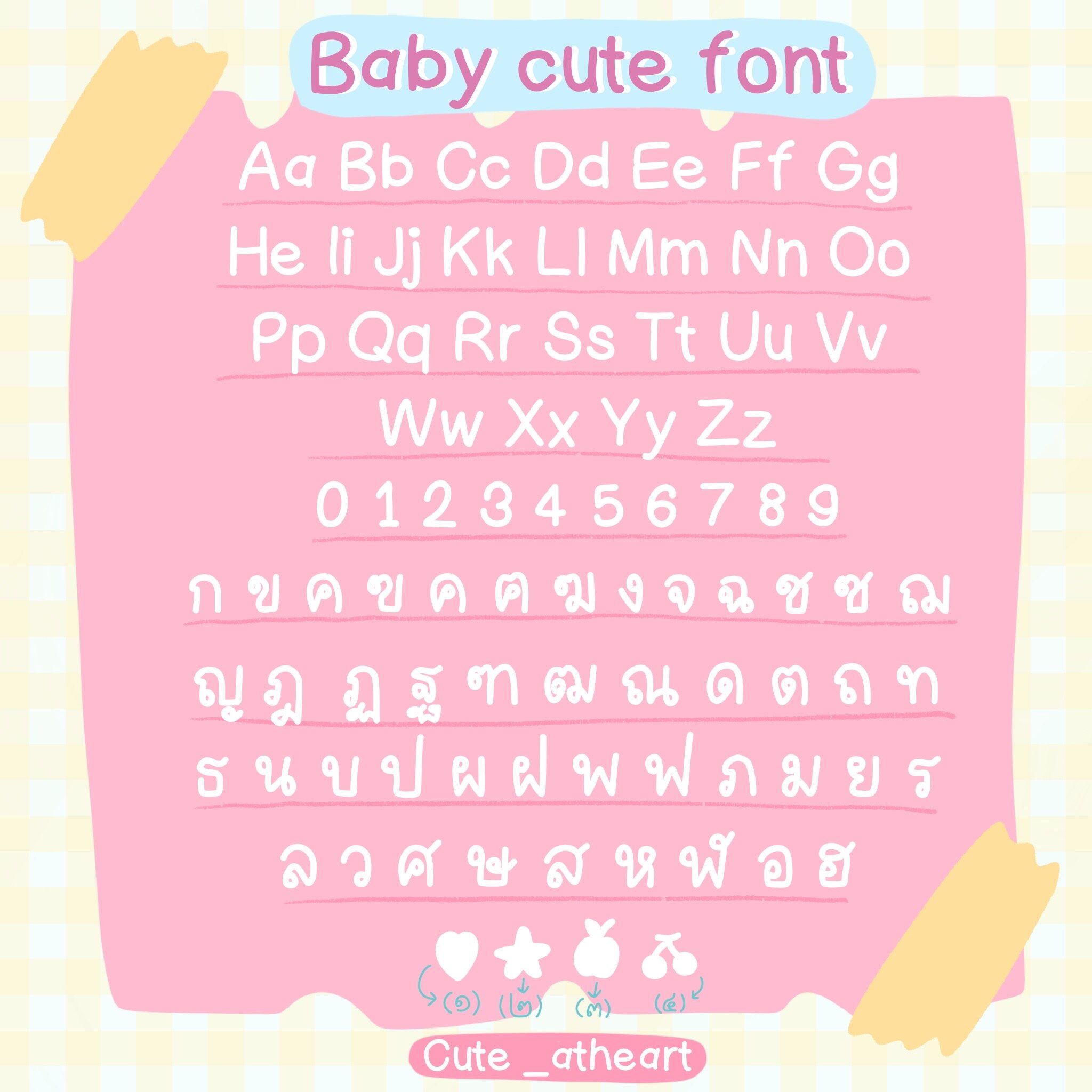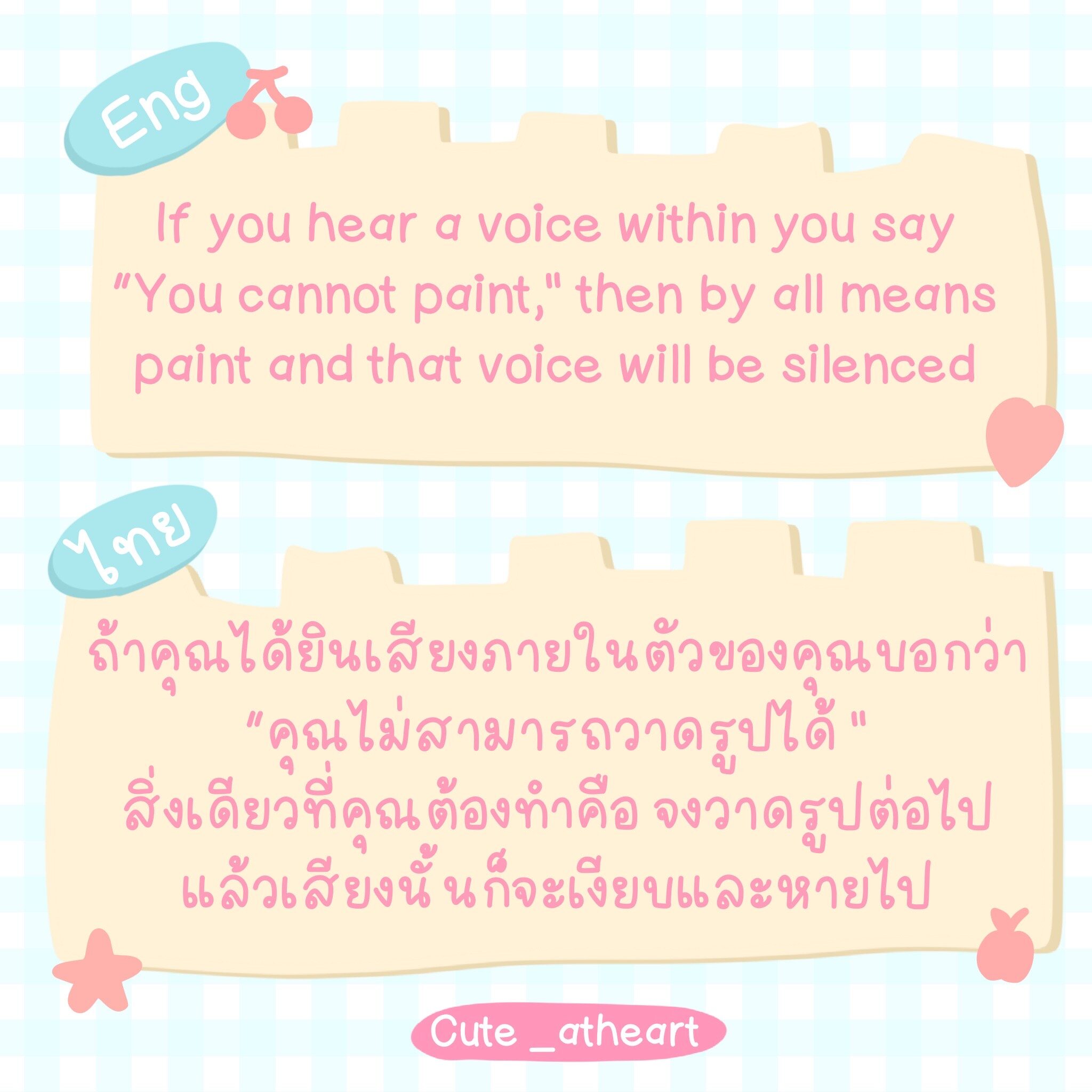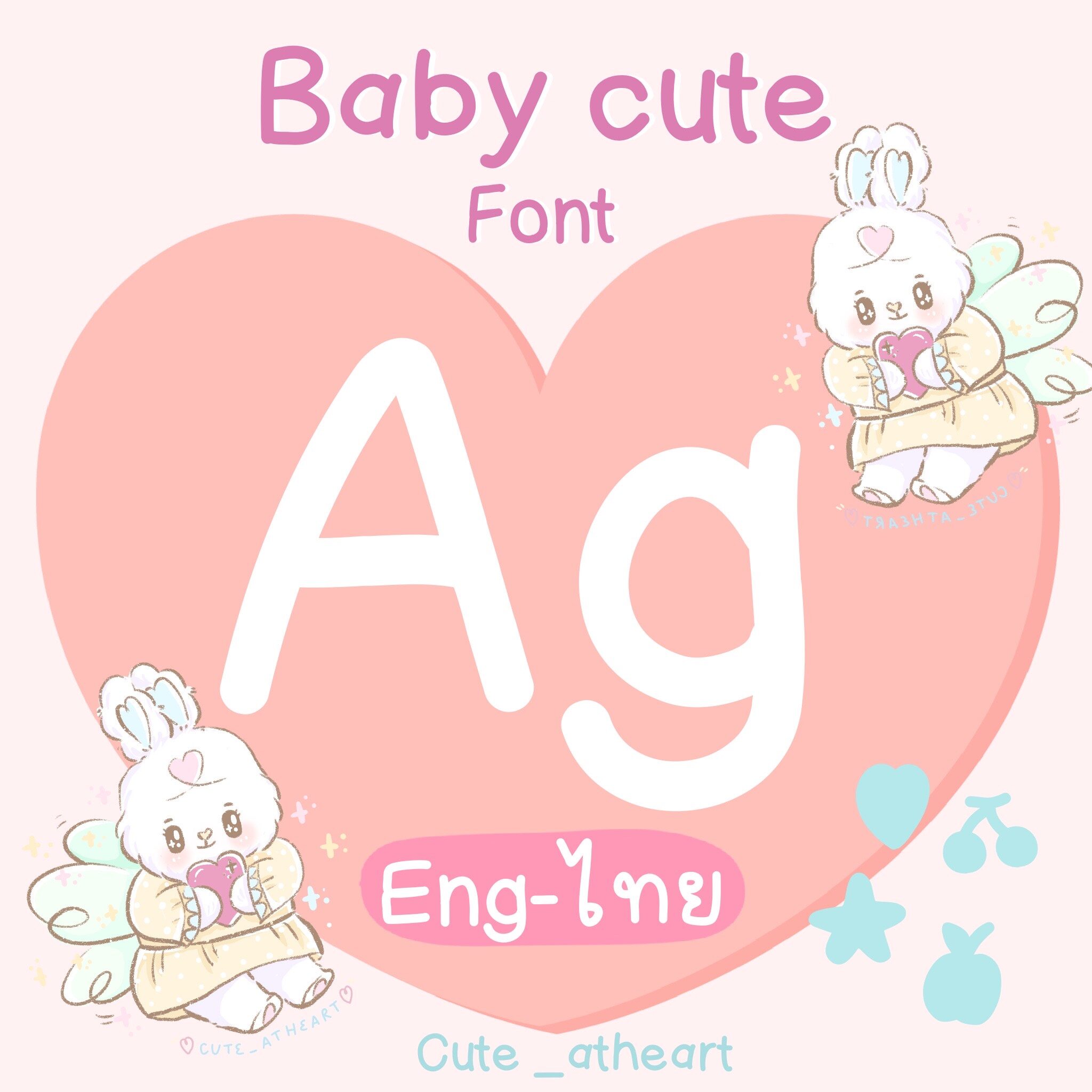
CUTE_ATHEART | FONT (baby cute)
– รายละเอียด
– ฟ้อนท์ลายมือน่ารัก ใช้ได้ทุกโอกาส
– มีภาษาไทย และภาษาอังกฤษ รวมถึง emoji พิเศษ (อยู่ที่เลข ๑ ๒ ๓ ๔)
– สระ วรรณยุกต์ ไม่ลอย